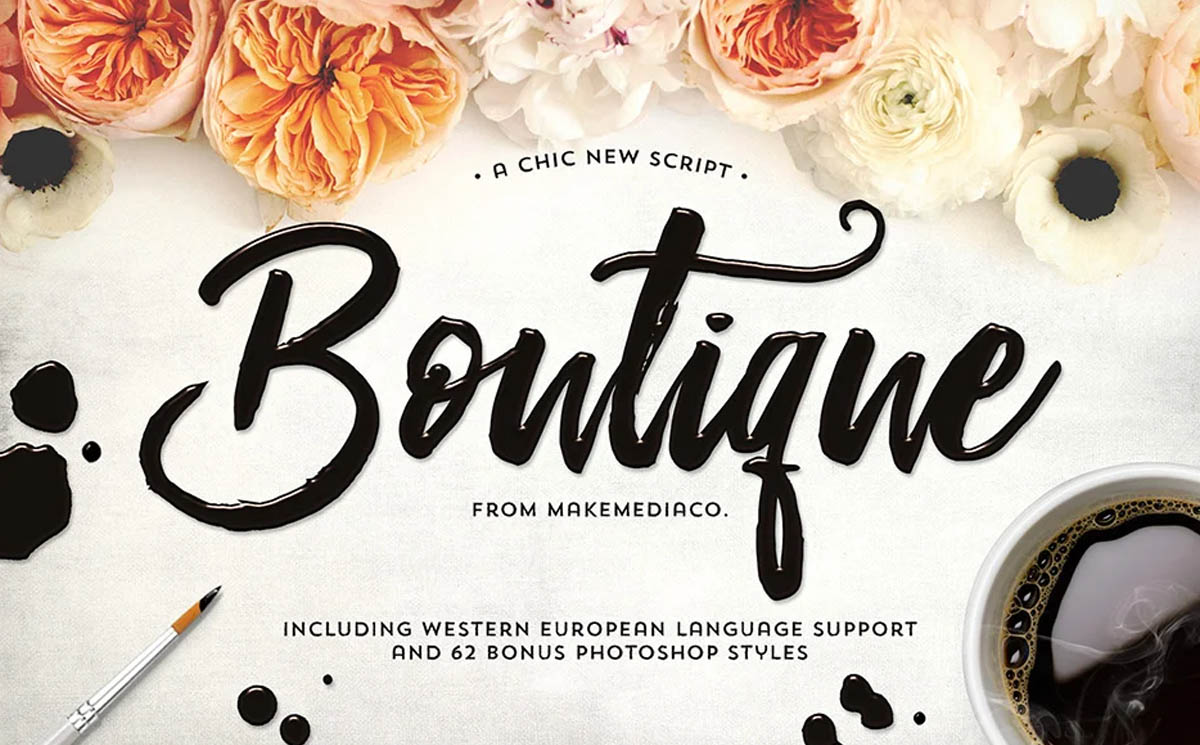
Font chữ viết tay Việt hóa SVN-Boutique Script là một trong những bộ phông chữ calligraphy cao cấp được cộng đồng thiết kế đồ họa tại Việt Nam đánh giá rất cao nhờ vẻ đẹp uyển chuyển, mềm mại và vô cùng sang trọng. Với sự kết hợp hoàn hảo giữa đường nét nghệ thuật thủ công tinh tế và tính ứng dụng đa dạng, bộ font này mang đến làn gió mới cho các dự án nhận diện thương hiệu, thiệp cưới, bao bì sản phẩm và truyền thông mạng xã hội. Nếu bạn đang tìm kiếm một font chữ độc đáo để nâng tầm giá trị thẩm mỹ cho các ấn phẩm thiết kế của mình, SVN-Boutique Script chắc chắn là sự lựa chọn hoàn hảo không thể bỏ qua.
Font Chữ Viết Tay Việt Hóa SVN-Boutique Script: Giải Pháp Thiết Kế Sang Trọng Và Tinh Tế
Trong lĩnh vực thiết kế đồ họa hiện đại, việc lựa chọn font chữ phù hợp đóng vai trò quyết định đến 80% sự thành công và tính thẩm mỹ của một ấn phẩm truyền thông. Font chữ viết tay Việt hóa SVN-Boutique Script nổi bật lên như một biểu tượng của sự thanh lịch, quý phái và mang đậm dấu ấn cá nhân. Được việt hóa một cách tỉ mỉ từ tác phẩm Boutique Script nguyên bản, bộ font giữ nguyên trọn vẹn những đường nét uốn lượn nghệ thuật cùng hệ thống ký tự phụ (alternates) phong phú, giúp các nhà thiết kế dễ dàng sáng tạo ra những tác phẩm typography ấn tượng.
Khác biệt hoàn toàn so với các font chữ viết tay thông thường dễ bị lỗi hiển thị khi gõ tiếng Việt có dấu, SVN-Boutique Script đã được tối ưu hóa kỹ lưỡng từng dấu thanh và dấu mũ. Điều này giúp tổng thể văn bản luôn giữ được sự cân đối, hài hòa và vô cùng chuyên nghiệp. Dù bạn áp dụng trong phong cách thiết kế cổ điển (vintage), tân cổ điển hay phong cách hiện đại tối giản (minimalism), font chữ viết tay Việt hóa SVN-Boutique Script vẫn phát huy tối đa sức hút thị giác đặc biệt của mình.
1. Hỗ Trợ Tiếng Việt Đầy Đủ Với Ký Tự Việt Hóa Chuẩn SEO
Điểm cộng lớn nhất của font chữ viết tay Việt hóa SVN-Boutique Script chính là khả năng hiển thị tiếng Việt hoàn hảo trên mọi nền tảng. Toàn bộ các dấu câu, dấu thanh (sắc, huyền, hỏi, ngã, nặng) và các chữ cái đặc trưng của tiếng Việt như ă, â, ê, ô, ơ, ư đều được căn chỉnh kỹ lưỡng về độ cao, khoảng cách và độ nghiêng. Nhờ đó, hiện tượng đè dấu, dính chữ hay lệch khoảng cách ký tự hoàn toàn bị loại bỏ, mang đến cho bạn trải nghiệm gõ văn bản mượt mà, chuẩn xác tuyệt đối trên cả bản in lẫn màn hình kỹ thuật số.
2. Đường Nét Mềm Mại, Nét Bút Chặt Chẽ Và Tự Nhiên
SVN-Boutique Script mô phỏng chân thực kỹ thuật viết chữ nghệ thuật bằng bút mực ngòi mềm (calligraphy). Cấu trúc chữ sở hữu những nét thanh nét đậm xen kẽ nhịp nhàng, tạo nên hiệu ứng thị giác vô cùng sống động và tự nhiên như được viết trực tiếp bằng tay. Sự kết hợp giữa các đường nhát bút uốn lượn uyển chuyển và phần đuôi chữ kéo dài nghệ thuật giúp các tác phẩm thiết kế trở nên bay bổng, có chiều sâu và truyền tải cảm xúc chân thành, ấm áp đến người xem.
3. Tích Hợp Hệ Thống Alternates Và Ligatures Đa Dạng
Không dừng lại ở các ký tự cơ bản, font chữ viết tay Việt hóa SVN-Boutique Script còn sở hữu kho ký tự thay thế (stylistic alternates) và ký tự nối (ligatures) vô cùng phong phú. Nhờ tính năng OpenType hiện đại, người dùng có thể linh hoạt biến tấu các chữ cái đầu câu hoặc cuối từ thành những nét uốn lượn phá cách. Điều này giúp các nhà thiết kế dễ dàng tạo ra những logo dạng chữ (wordmark) độc bản, tiêu đề bài viết cá tính mà không lo đụng hàng hay trùng lặp ý tưởng.
4. Khả Năng Ứng Dụng Đa Dạng Trên Nhiều Lĩnh Vực Thiết Kế
Nhờ sở hữu vẻ đẹp đa năng và đẳng cấp, phông chữ SVN-Boutique Script được ứng dụng rộng rãi trong nhiều loại hình sản phẩm sáng tạo khác nhau. Bạn có thể sử dụng font chữ này để thiết kế bộ nhận diện thương hiệu cho ngành thời trang, mỹ phẩm, spa cao cấp, hoặc dùng trong các ấn phẩm sự kiện như thiệp cưới, thiệp sinh nhật, menu nhà hàng và bìa sách nghệ thuật. Ngoài ra, phông chữ này cũng là công cụ đắc lực cho các sáng tạo nội dung trên mạng xã hội như thiết kế hình ảnh trích dẫn (quotes), banner quảng cáo Facebook, Instagram hay thumbnail YouTube thu hút sự chú ý.
5. Tương Thích Hoàn Hảo Trên Mọi Phần Mềm Đồ Họa Hàng Đầu
Ưu Điểm Vượt Trội Khi Sử Dụng SVN-Boutique Script Trong Các Dự Án Sáng Tạo
Khi đầu tư thời gian vào việc lựa chọn font chữ cho dự án, các designer chuyên nghiệp luôn ưu tiên các bộ phông chữ vừa đáp ứng tính thẩm mỹ vừa đảm bảo hiệu quả truyền thông. SVN-Boutique Script tự hào đáp ứng trọn vẹn các tiêu chí khắt khe đó nhờ những ưu thế nổi bật:
- Tăng giá trị thương hiệu: Nét chữ uốn lượn tinh tế giúp thương hiệu thể hiện sự chuyên nghiệp, đẳng cấp và gu thẩm mỹ khác biệt vượt trội so với đối thủ cạnh tranh.
- Tiết kiệm thời gian thiết kế: Với hệ thống nét uốn và ký tự nối tích hợp sẵn, bạn có thể tạo ra các tác phẩm chữ nghệ thuật đẹp mắt trong thời gian ngắn mà không cần mất công vẽ lại từng nét thủ công.